回望2024,方正字库走过了不平凡的一年。这一年,我们携手设计师、合作厂商与广大品牌及用户,一同挖掘字体的魅力与潜力。
从产品到服务,从技术到市场,字体设计在不断拓宽的应用边界和不断丰富的创新创造中绽放光彩。这份年终报告,将记录我们探索的足迹,分享字体世界的精彩故事,解锁字体的更多可能性。
新产品
New Fonts
2024年,方正字库官网总计上线300余款中文字体,涵盖了创新经典的基础字体,传承书法精髓的书写字体,个性独特的创意字体和创意书写。风格多样的新字体,能够满足包装、广告、视频等多领域的用字需求,为设计作品提供无限的创想可能。此外,方正字库自主研发的西文字体FT DIN上线官网,标志着我们在满足中国市场对高品质西文字体需求方面迈出了坚实的一步。
与此同时,方正字库积极将具有鲜明中国文化特色的精品字库开发为适合其他国家和地区使用的语言文字,推动中国汉字文化“走出去”。目前,方正字库已实现方正颜真卿楷书等多款中华精品字库的日文版开发,以及方正少林功夫体的日文、韩文字体出海。
2024奖项回顾
近年来,方正字库精心研发的新字体不仅赢得了市场的青睐,更在业界内收获了极高赞誉。今年,方正字库多款精品字体产品荣获多个权威荣誉奖项,这些字体产品以其独特的创意理念、精湛的设计技巧以及对文化深度的精准捕捉,成为了引领字体设计新风尚的标杆。
方正少林功夫体 获第十七届中国之星设计奖形象设计类(字体设计类)金奖、第13届 GRANSHAN 字体设计大赛中文组一等奖、Tokyo TDC Annual Awards 2024优秀作品提名奖;
方正CDS拙金体 获第十七届中国之星设计奖形象设计类(字体设计类)银奖
方正华思楷宋、方正华思刻线 获第十七届中国之星设计奖形象设计类(字体设计类)优秀奖。
方正华思楷宋
方正华思刻线
方正灵飞刻石 获第十七届中国之星设计奖形象设计类(字体设计类)铜奖、Tokyo TDC Annual Awards 2024优秀作品提名奖;
方正极黑 获第13届 GRANSHAN 字体设计大赛中文组二等奖。
新合作
New Partnership
2024年,方正字库与Monotype、TypeTogether、Production Type、Fontworks、视觉设计研究所(VDL)、Motoya等国际知名字库厂商合作持续加深,外文字体上线总数累计达13630款。
方正字库提供全球95%以上语言的字体,给中国设计师提供更丰富的用字选择,给中国企业提供更全面的字体解决方案。
方正字库 × TypeTogether
今年,方正字库与国际字体伙伴TypeTogether的合作更加紧密,引进Postea-A、Postea-F、Tablet-H等专为国内应用市场最新开发的优质西文字体,为中国品牌和设计师带来更加丰富、更具适用性和更高性价比的产品选择。
方正字库×Fontworks
今年,方正字库与老朋友Fontworks合作不断加深。目前,在方正字库可买到237款Fontworks字体产品,最新中文化合作字体“方正FW马蒂斯”也已上线官网。今年年底,Fontworks市场推销部部长太田昌宏应邀参与方正字库首场海外品牌发布活动“汉字对话——方正字库2024东京发布会”并表题为《与方正同行》的演讲,展现了方正字库与Fontworks之间深厚的合作关系。
Fontworks中文化新字体 方正FW马蒂斯
方正字库 × VDL
今年,方正字库与日本株式会社视觉设计研究所(Visual Design Laboratory)进一步建立深度合作,全线引进VDL系列日文字体,28个字体家族总计170款日文字体正式上线方正字库官网和电脑客户端,携手提供更加专业、适应时代和环境需求的字体服务。此外,方正字库根据中国国家文字规范笔形,对14款VDL日文家族字体进行中文化开发,目前已有方正VDL哥特明朝、方正VDL建筑黑等9个字体及字体家族上线,满足国内设计师更多的用字需求。(点此了解合作详情)
方正字库 × 欣喜堂
今年,方正字库与日本活字书体字体设计公司欣喜堂(Kinkido)进一步开展中文化字体合作,目前,最新开发的方正武英、方正陈起体已正式上线方正字库官网,让中华古籍刻本的字体魅力在新时代得以传承与焕发新生,续写着千年文化的悠远韵味。
方正武英
方正陈起体
方正字库 × Motoya
今年,方正字库与日本老牌字体厂商Motoya展开合作,引进125款Motoya字体产品,为国内设计师提供丰富的字体选择。Motoya字体的开发始于20世纪50年代,一直延续至今,尽管经历了多种排版手段的变迁和产品形式的变化,但不变的是Motoya对“可读性”和“文字美感”的追求。
モトヤマルベリ
Sモトヤ行書
モトヤ古印体
方正字库 × 精美堂
今年,方正字库与日本厂商精美堂展开“勘亭流”字体中文化开发合作。精美堂在日本已有超过120年的历史,专注于提供高质量的字体和广告制作服务。勘亭流是一种常用于歌舞伎看板的字体,设计独特而富有表现力,适合用于各种创意项目。
方正精美堂勘亭流
方正字库 × 砧書体制作所
今年,方正字库与日本砧书体制作所联合推出的中文化产品——方正砧书圆正式上线方正字库官网。方正砧书圆是一款具有篆书特点的圆体字,带有悠久时光流淌的宁静和可爱的温柔之感。砧书体制作所由片岡朗成立,旨在制作不受常识束缚的独特字体的同时,传承文字的传统。
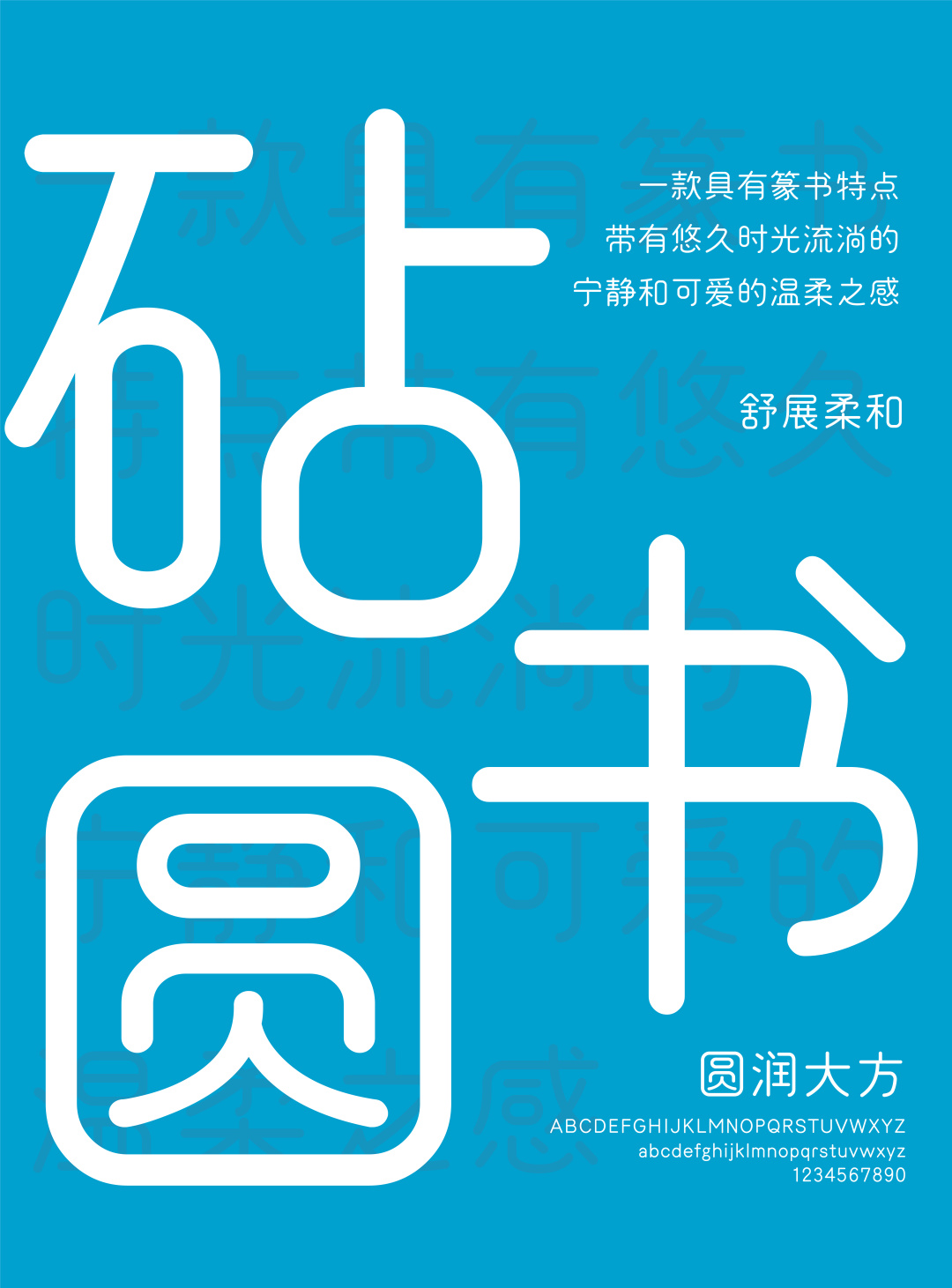
方正砧书圆
方正字库 × IWATA
今年,方正字库与日本字体厂商IWATA合作开发中文化产品——方正Iwata福丸体,字体源于日本岩田福丸字体,其主题是 “让未来 100 年都喜欢的字体 ”和 “可爱而优雅”。IWATA岩田公司自 1920 年创立以来,始终坚持的造字的态度,不断开发出符合时代需求的字体。
方正Iwata福丸体
新服务
New Services
2024年,除了字体定制服务的持续深化,方正字库还通过深入挖掘各行业领域的字体应用需求与趋势,为企业和品牌提供系统性的字体解决方案,满足市场日益精细化的字体使用要求,推动行业品牌建设与内容传播的高效升级。
营销字体推荐
今年,方正字库通过广泛收集品牌营销用字案例,为广大品牌针对性总结了巴黎奥运会、端午节、儿童节、七夕节、国庆节等10个品牌热门营销节点的字体推荐方案,赋能品牌市场营销推广,并通过工作坊、客户服务群等方式向客户普及专业字体知识,解决字体使用中的实际问题,为产品及品牌的商业宣传打造更具吸引力和专业性的视觉效果。
行业用字服务
今年,方正字库持续深耕行业细分服务,为特定行业开发适合信息显示需求的专用字体,并通过行业联合起草相应的文字使用规范,使行业用字更加规范化、标准化;通过广泛收集行业用字案例、分析行业用字现状,深入研究并总结了不同行业的众多企业及品牌的最新用字趋势和需求。
在汽车行业的字体服务实践中,方正字库开发了专门为车载视觉信息显示设计的字体——方正悦驾黑;携手中国汽车工程学会,及中国第一汽车集团有限公司等17家汽车制造商、服务商,联合起草发布了《车载视觉信息汉字显示规范》。此外,方正字库还为广电行业、游戏行业、食品行业、日化行业、文旅行业、金融行业等多个行业领域撰写了行业字体解决方案,帮助各行各业系统且有针对性地处理字体使用问题。
新活动
New Activities
2024年,方正字库凝聚深厚底蕴与前瞻视野,积极投身于丰富多彩的市场活动及行业建设中,广泛传播着字体设计与汉字文化的独特魅力。
同时受邀出席了众多行业的顶尖论坛与展览,与各界精英深入交流,为不同领域提供了创意灵感与技术赋能,进一步拓宽了中文字体应用的边界,促进了字体与各行各业的融合发展。
12月20日-22日,2024年海南国际知识产权交易大会在海口隆重召开。方正字库以“中华精品字库”、经典中文字体、全球化多语种字体、专业定制服务、人口信息生僻字解决方案以及知识产权创新技术工具等亮相展会。
12月3日,方正字库在中共北京市海淀区委宣传部、北京市海淀区文化发展促进中心举办的“2024海淀文化创意大赛”中以参赛作品《AI在中华精品字库设计中的应用》荣获AI海淀&文化强区赛道一等奖,生动展示了方正字库在运用AI助力书法文化创新和汉字文化传播方面的努力。
11月30日,方正字库作为主任单位支持“中国中文信息学会汉字字形信息专业委员会2024年学术研讨会”成功举办,促进字体行业内部深度沟通交流,推动中文字形信息学科的发展。
11月27日至12月20日,方正字库与深圳市平面设计协会(SGDA)等单位联合举办“圆象⽅仪·字蕴新⽣——2024字生态设计展”系列活动,促进学术研究与商业实践的结合,推动文字文化的传承与创新。
11月22日,方正字库首场海外品牌发布活动“汉字对话——方正字库2024东京发布会”在东京成功举办。活动以“汉字”为载体,通过多位中日嘉宾的专业分享,全面呈现了方正字库在汉字创新研究与字体设计方面的成果,呈现了方正字库与Fontworks之间深厚的合作关系,为中日两国汉字及字体设计领域的合作与沟通搭建了重要平台。
11月22日,方正字库作为第一批贯标示范企业代表,受邀参加“语言文字技术供需对接大会暨强制性国家标准GB 18030-2022第1号修改单宣贯会”并发表主题演讲,展示了方正字库在参与制定、贯彻执行国家标准,以及推动《方正人口信息生僻字解决方案》建设方面做出的相关工作。
11月5日,“第三届汽车海外车联网高峰论坛”在上海举行。方正字库应邀出席并以《字体,汽车出海的重要力量》为主题发表演讲,围绕字体在汽车行业中的应用与影响力,向与会嘉宾展示了方正字库在助力汽车品牌全球化进程中的创新与实践。
9月21日,“新视界·新启航——方正2024字体设计大会”在UCCA(北京)尤伦斯当代艺术中心成功举办。方正字库《2025字体趋势报告》隆重发布,深度解读未来字体设计趋势;2024年最新字体产品精彩推出;第十三届『方正奖』设计大赛正式启动;众多行业资深专家与崭露头角的新生代设计师共聚一堂,跨世代深入交流、碰撞智慧火花。
9月20日至26日,方正字库亮相“2024河北国际工业设计周”,以「中国人,方正字」为主题生动呈现了文字的现代演绎和美学设计;在新消费创意设计圆桌会,带来《字体的力量:如何用字体设计传达品牌灵魂》主题演讲,深入分享了字体设计在商业品牌塑造中的重要作用和方正字库在品牌定制字体的突出实践。
8月22日,方正字库受邀参加“第三十一届北京国际广播电影电视展览会(BIRTV2024)‘新质与未来’影像创作论坛”并发表演讲,以方正字库为2024总台龙年春晚打造的定制字体“春晚龙行体”为基点,从字体的专业角度剖析本次2024总台龙年春晚视觉新体验的变化与革新,展示了方正字库能够为广电客户提供的定制字体及相关优质字体服务。
方正字库《2025字体趋势报告》报告基于2024年8月开展的“方正字库字体趋势问卷调查”统计数据,从当今日渐复杂的消费群体类型和消费场景背景切入,解读未来消费者对字体的需求趋势。
《2025字体趋势报告》揭秘了自然归真、中式美学、经典品质、文化共渐、未来幻想、赛博朋克、潮流醒目、复古摩登、市井烟火、软萌治愈、节奏运动等11项未来的字体风格趋势,通过解析不同消费人群在字体风格上的多元需求,为现代字体设计和应用提供更具针对性和创新性的洞见。
此外,《2025字体趋势报告》还总结了AI智能匹配,AI智能生成,可变字体,OpenType以及云端字库等方面的字体技术趋势;定制服务细分化和行业服务深度化的字体服务趋势;行业共建、产学结合、兴趣社团等行业趋势。方正字库期待用更加科学和理性的字体趋势研究成果,来指导未来字体设计开发和应用的方向,为字体设计者、创作者、平面设计师以及广大用户带来灵感和参考。